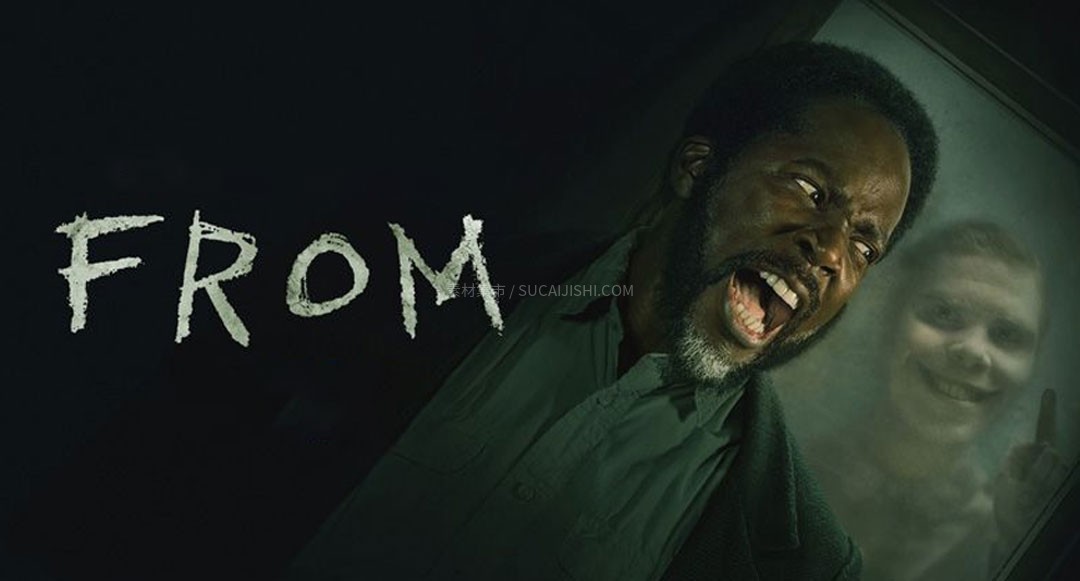
《梦魇绝镇》同款风格:Afraid 悬疑恐怖手绘字体
寻找美剧《梦魇绝镇》那种令人毛骨悚然的视觉感?这款 Afraid 字体完美复刻了原剧定制字体的精髓。它带有扭曲、颤抖的手绘线条,仿佛是受害者在绝望中刻下的痕迹。无论是夜间出没的“微笑怪物”,还是小镇无法逃离的诅咒,这款字体都能精准传达出那股克苏鲁式的压抑氛围。